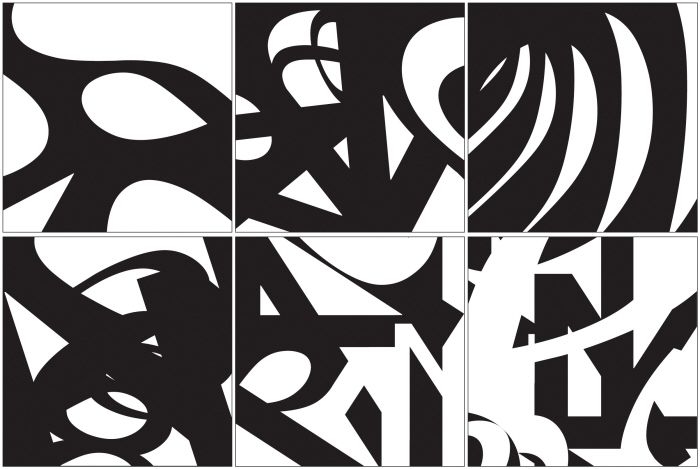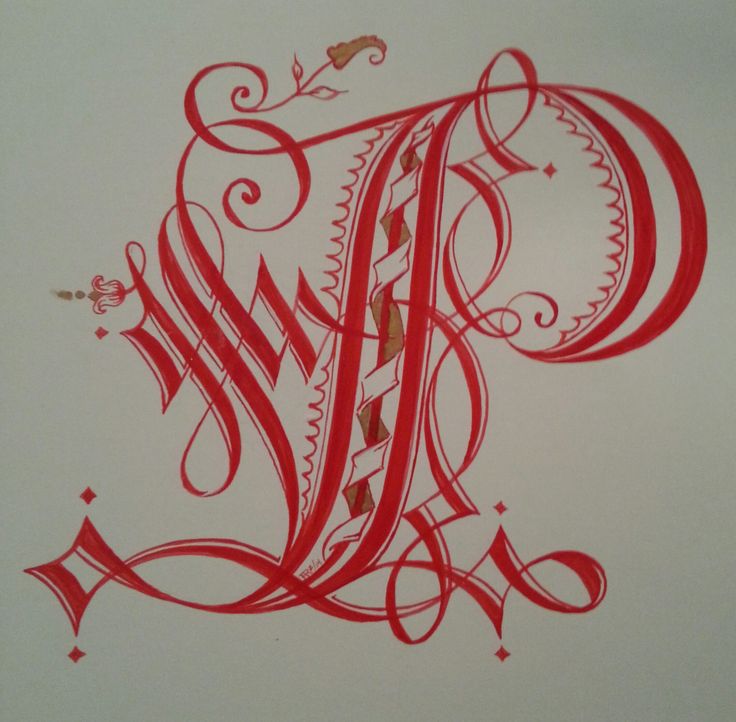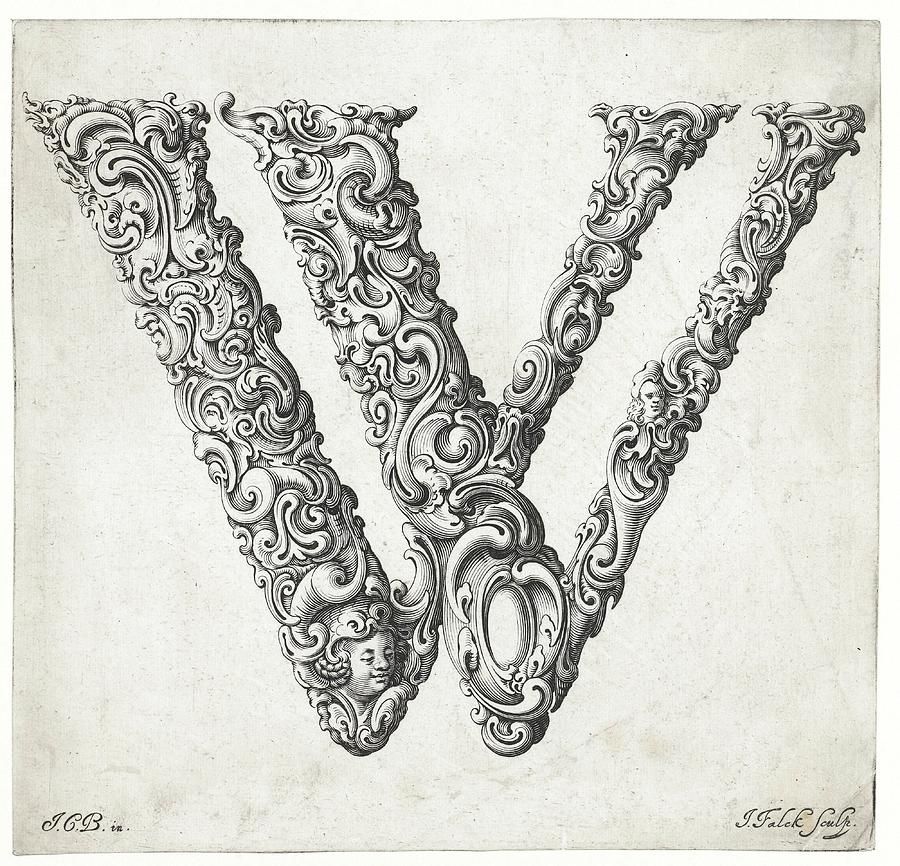
6.Буква- строка-шрифт. Искусство шрифта.
Искусство
шрифта.
Цвет
Форма
основные принципы
единство
контраст
баланс
Компьютерный дизайн
Компьютерный дизайн чрезвычайно
объемная сфера практического дизайна,
включающая в себя следующие области:
собственно графику;
полиграфический дизайн;
электронные издания;
Web-дизайн;
трехмерную графику
7. Искусство шрифта
Свободные формы – пятна и линии, как мывыяснили, воздействуют только ассоциативнообразно и никакой конкретной информации не
несут. Однако есть состоящие из линий
абстракции, которые имеют конкретный смысл.
Это буквы.
8. История шрифта
• Пиктограмма — картинное, или рисуночноеписьмо в виде наскальных рисунков у
первобытных людей
П., учитель ИЗО, ГОУ «Центр образования» №1470, 2010 г.9. Любая буква или иероглиф прежде всего изображение. Буква ведет свою родословную от рисунка. В глубокой древности всю информацию
обозначали рисунками. Потомрисунки превратились в первые буквенные символы,
которые и стали основой написания современных букв.
На смену пиктографическому письму пришло и
деографическое. Предметы изображались либо
символическими знаками (солнце, луна), либо
графическими изображениями: птица, зверь и т.
Буквенно-звуковое письмо
появилось во втором
тысячелетии до н.э. В нем
знаки означали отдельные
звуки (фонемы). Причем
знаки в зависимости от
произношения могли поразному передавать
звуковые особенности
языка. В буквенно-звуковом
письме с помощью
графических знаков можно
было передавать
человеческую речь
П., учитель ИЗО, ГОУ «Центр образования» №1470, 2010 г.С течением времени графические знаки усовершенствовались,
на смену одним приходили другие, более простые по форме,
передающие новое значение.
Шрифт (или
шрифтовая гарнитура)- это буквы,
объединенные одним стилем графического начертания.
Сравните шрифты придуманные разными дизайнерами…
Под рукой художника-дизайнера буквы приобретают форму и
пропорции, свойственные только данному шрифту. От того, каким
шрифтом, каким кеглем (т.е. размером шрифта) написано слово,
зависит и его восприятие. На нас воздействует не только смысл
слова, но и характер шрифта.
• Шумерское письмо
• Египетское письмо
• Греческое письмо
Основные варианты
разбивки заголовка
Вариант разбивки
большого заголовка
П., учитель ИЗО, ГОУ «Центр образования» №1470, 2010 г.• Акцентирование размером и
насыщенностью
• Зависимость ритмического строя
от величины межбуквенных пробелов
Основными называют штрихи, определяющие основы букв
(прямые и кривые, вертикальные и наклонные, тонкие и толстые).
Соединительными штрихами называют элементы, соединяющие
Вот краткое описание каждого из этих настроений:
Современный: Такое ощущение, что оно было создано для 21 века и не имело бы смысла в любой другой период. Обычно чистый, более минималистичный и отлично подходит для проектов, требующих более изысканного вида.
Удар: Удар. Смелость. Масса. Эти пары шрифтов тянутся к вам, захватывают вас и втягивают в свое сообщение.